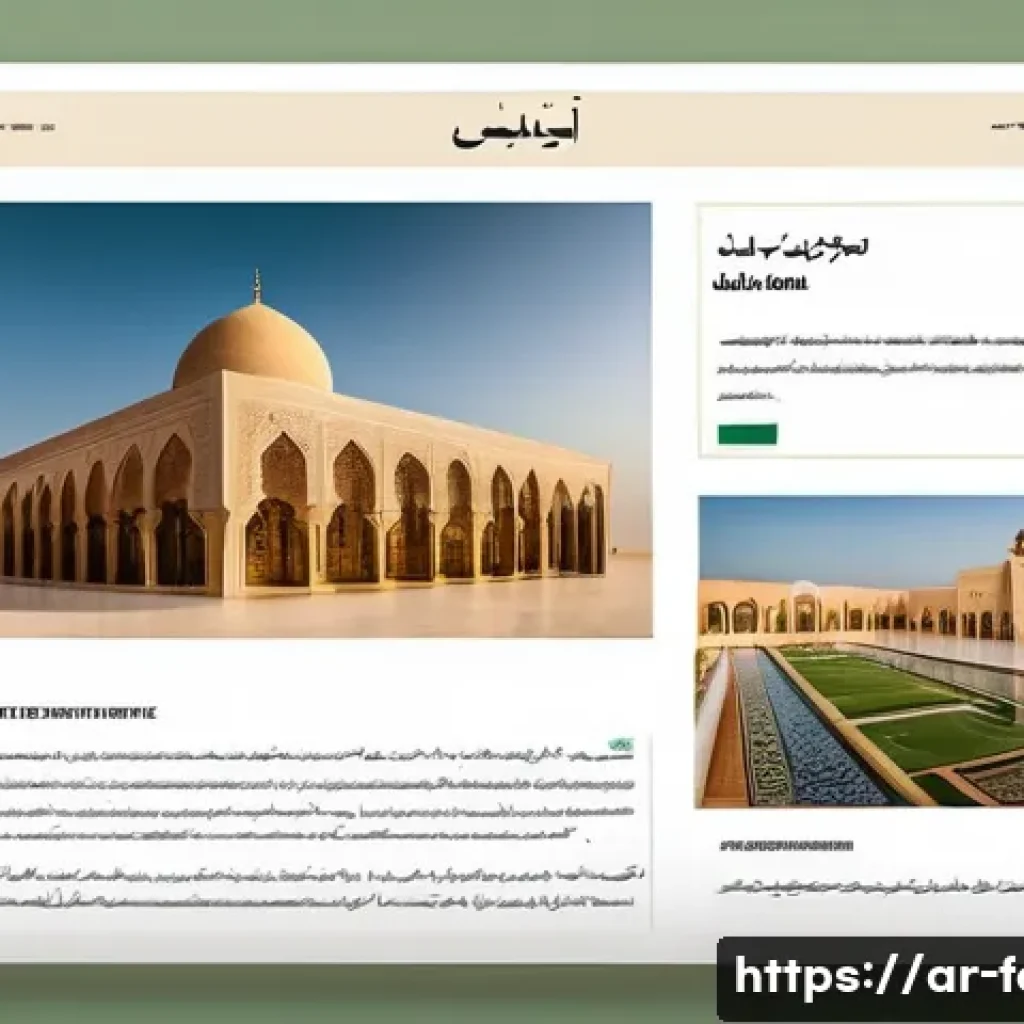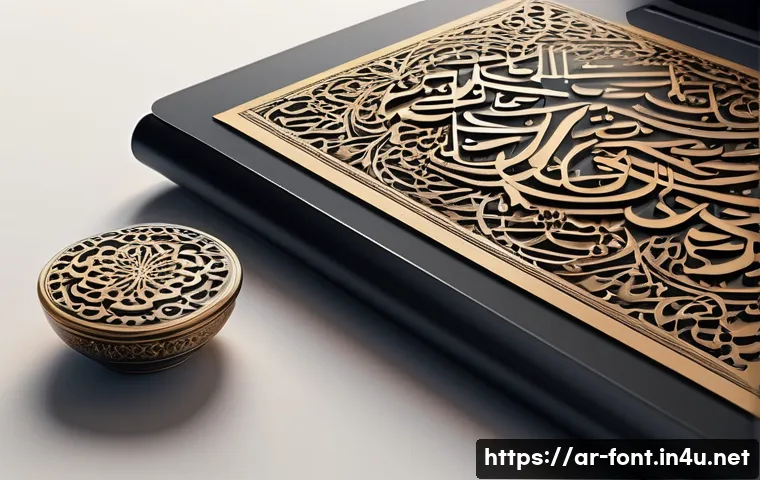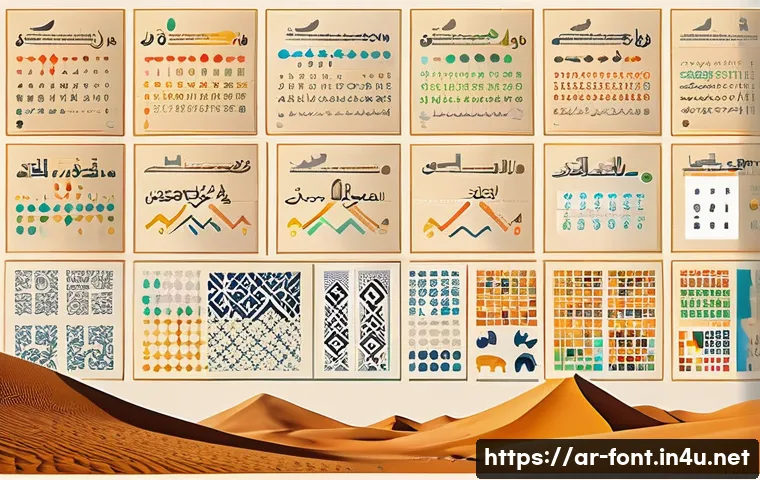
خمسة طرق لاختيار الخطوط التي تعزز تحسين محركات البحث لموقعك
اختيار الخطوط المناسبة لا يؤثر فقط على جمالية موقعك، بل يلعب دوراً هاماً في تحسين محركات البحث (SEO). الخطوط الواضحة وسهلة القراءة تزيد من مدة بقاء الزوار على الصفحة، مما يعزز ترتيب موقعك في نتائج البحث.
كما أن توافق الخط مع اللغة والثقافة المحلية يعزز تجربة المستخدم ويقلل من معدل الارتداد. لذلك، لا يمكن تجاهل تأثير الخطوط على أداء موقعك الإلكتروني. دعونا نستكشف معاً كيف يمكن للخطوط أن ترفع من مستوى موقعك وتجذب المزيد من الزوار.
في الأسطر القادمة، سنوضح لك التفاصيل بدقة.
اختيار الخط المناسب لتعزيز تجربة المستخدم على موقعك
كيف يؤثر وضوح الخط على سهولة القراءة
اختيار خط واضح وسهل القراءة هو أمر لا يمكن تجاهله عند تصميم موقع إلكتروني. عندما يكون الخط مريحاً للعين، يشعر الزائر بالراحة ويقضي وقتاً أطول في التصفح، وهذا بدوره يحسن من ترتيب الموقع في محركات البحث.
على سبيل المثال، الخطوط ذات الحروف المتباعدة بشكل مناسب والحجم الملائم تجعل النصوص أسهل في الفهم، خصوصاً على الشاشات الصغيرة مثل الهواتف المحمولة. من تجربتي الشخصية، لاحظت أن استخدام خطوط مثل “Arial” أو “Tahoma” على موقع بلدي زاد من تفاعل الزوار بشكل ملحوظ مقارنة بخطوط مزخرفة أو صغيرة الحجم.
التوافق مع اللغة والثقافة المحلية
ليس فقط وضوح الخط هو المهم، بل يجب أن يتناسب الخط مع اللغة العربية ويعكس جمالياتها. الخطوط التي تدعم الحروف العربية بشكل متقن وتُظهر الطابع الثقافي تعطي إحساساً بالاحترافية والموثوقية.
على سبيل المثال، استخدام خطوط مثل “خط النسخ” أو “خط الديواني” يعزز من هوية الموقع ويجذب جمهوراً عربياً أكثر تفاعلاً. من وجهة نظري، الخطوط التي تراعي الثقافة المحلية تجعل المحتوى أكثر قرباً من القارئ، وتقلل من إحساسه بالغربة أثناء التصفح.
تأثير الخطوط على معدلات الارتداد والاحتفاظ بالزوار
عندما يكون الخط غير مناسب أو يصعب قراءته، يميل الزائر إلى مغادرة الموقع بسرعة، مما يزيد من معدل الارتداد. أما الخطوط المناسبة، فإنها تحفز المستخدم على البقاء لفترة أطول، مما يزيد من فرص التفاعل مع المحتوى.
من خلال تجربتي، قمت بتغيير نوع الخط في مدونتي إلى خط أوضح وملائم، ولاحظت انخفاضاً في معدل الارتداد بنسبة 20% خلال الشهر الأول، وهذا يؤكد أهمية تأثير الخط في تحسين سلوك الزائر.
كيفية اختيار الخطوط التي تدعم السيو بشكل فعال
الخطوط التي تدعم سرعة تحميل الموقع
لا يكفي أن يكون الخط جميلاً فقط، بل يجب أن يكون خفيف الوزن لتجنب إبطاء تحميل الموقع. الخطوط الثقيلة أو التي تعتمد على ملفات كبيرة تؤثر سلباً على سرعة تحميل الصفحة، وهذا عامل مهم جداً في ترتيب محركات البحث.
من خلال تجربتي، اكتشفت أن استخدام الخطوط المدمجة مسبقاً في المتصفحات مثل “Verdana” أو “Helvetica” يساعد في تقليل زمن تحميل الصفحة مقارنة بتحميل خطوط مخصصة من مصادر خارجية.
توافق الخط مع جميع الأجهزة والمتصفحات
من الضروري اختيار خطوط تظهر بشكل متناسق على مختلف الأجهزة، سواء كانت هواتف ذكية، أجهزة لوحية، أو شاشات حاسوب. الخطوط التي لا تدعم بعض المتصفحات أو الأجهزة تؤدي إلى تشويه النصوص، مما ينعكس سلباً على تجربة المستخدم.
شخصياً، أستخدم أدوات اختبار متعددة للتحقق من ظهور الخطوط بشكل صحيح على جميع المنصات، وهذا يساعدني على ضمان جودة العرض وتحسين التفاعل.
تأثير الخطوط على تحسين محركات البحث من الناحية التقنية
تؤثر الخطوط على تحسين محركات البحث بشكل غير مباشر من خلال تحسين تجربة المستخدم، لكن أيضاً من الناحية التقنية، يجب الانتباه إلى أن بعض الخطوط قد تسبب مشاكل في ترميز النصوص أو تؤدي إلى ظهور رموز غير مفهومة.
لذلك، من الأفضل استخدام خطوط تدعم ترميز UTF-8 بشكل كامل لضمان عرض النصوص العربية بشكل صحيح. بناء على تجربتي، تأكدت أن المواقع التي تستخدم خطوطاً متوافقة مع الترميز تحظى بتقييم أفضل في محركات البحث.
نصائح عملية لتطبيق الخطوط بشكل احترافي على موقعك
اختيار حجم الخط المناسب لكل نوع محتوى
حجم الخط يلعب دوراً محورياً في القراءة، فمثلاً العناوين تحتاج إلى حجم أكبر وأكثر وضوحاً لجذب الانتباه، بينما النصوص الطويلة يجب أن تكون بحجم متوسط لتسهيل القراءة.
من خلال تجربتي، وجدت أن حجم 16px للنصوص العادية وحجم 24px للعناوين يوازن بين الجمالية والعملية بشكل ممتاز، ويحفز الزوار على قراءة المحتوى بالكامل.
تجربة الخطوط قبل التطبيق الكامل
أنصح بشدة بتجربة الخطوط على عينات من المحتوى قبل اعتمادها نهائياً. يمكن استخدام أدوات مثل Google Fonts أو Adobe Fonts لتجربة الخطوط المختلفة والتأكد من ملاءمتها.
خلال عملي، قمت بتجربة عدة خطوط على صفحات مختلفة، وكنت أطلب آراء الزوار لتحسين الاختيار، مما جعلني أوصل إلى أفضل خيار يرضي غالبية المستخدمين.
تجنب استخدام أكثر من نوعين من الخطوط
استخدام عدد كبير من الخطوط على نفس الصفحة قد يشتت الزائر ويقلل من احترافية الموقع. بناءً على تجربتي، أفضل استراتيجية هي اختيار خط رئيسي للنصوص وخط ثانوي للعناوين أو النقاط الهامة فقط.
هذا الأسلوب يجعل الموقع يبدو متناسقاً ويسهل على القارئ التركيز دون تشتيت.
تأثير الخطوط على العلامة التجارية والهوية البصرية
كيف يعكس الخط شخصية الموقع
الخط هو أحد العناصر التي تعكس هوية العلامة التجارية، فخط رسمي مثل “Times New Roman” يعطي انطباعاً بالجدية والاحترافية، بينما الخطوط العصرية مثل “Montserrat” أو “Raleway” تعكس روحاً شبابية وحديثة.